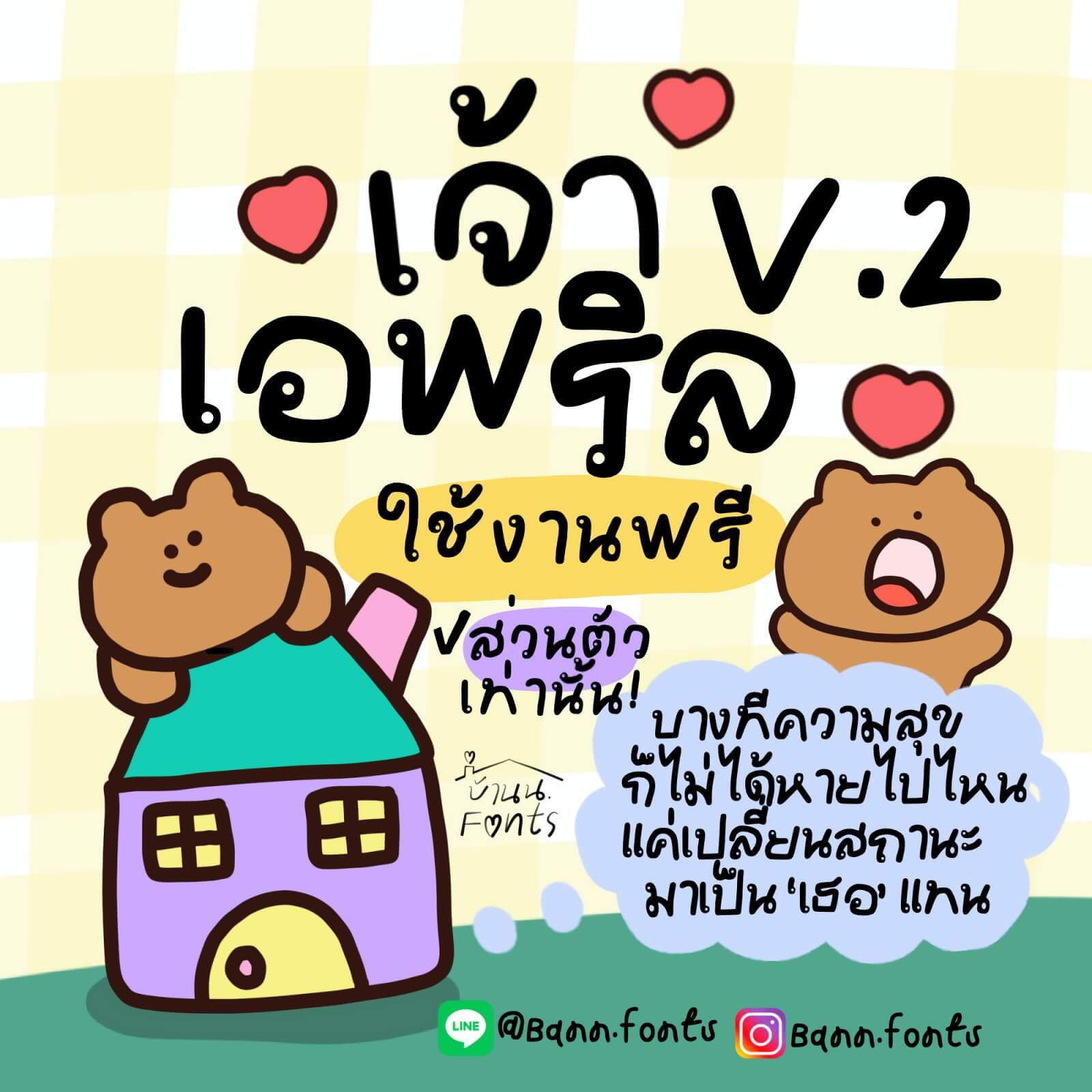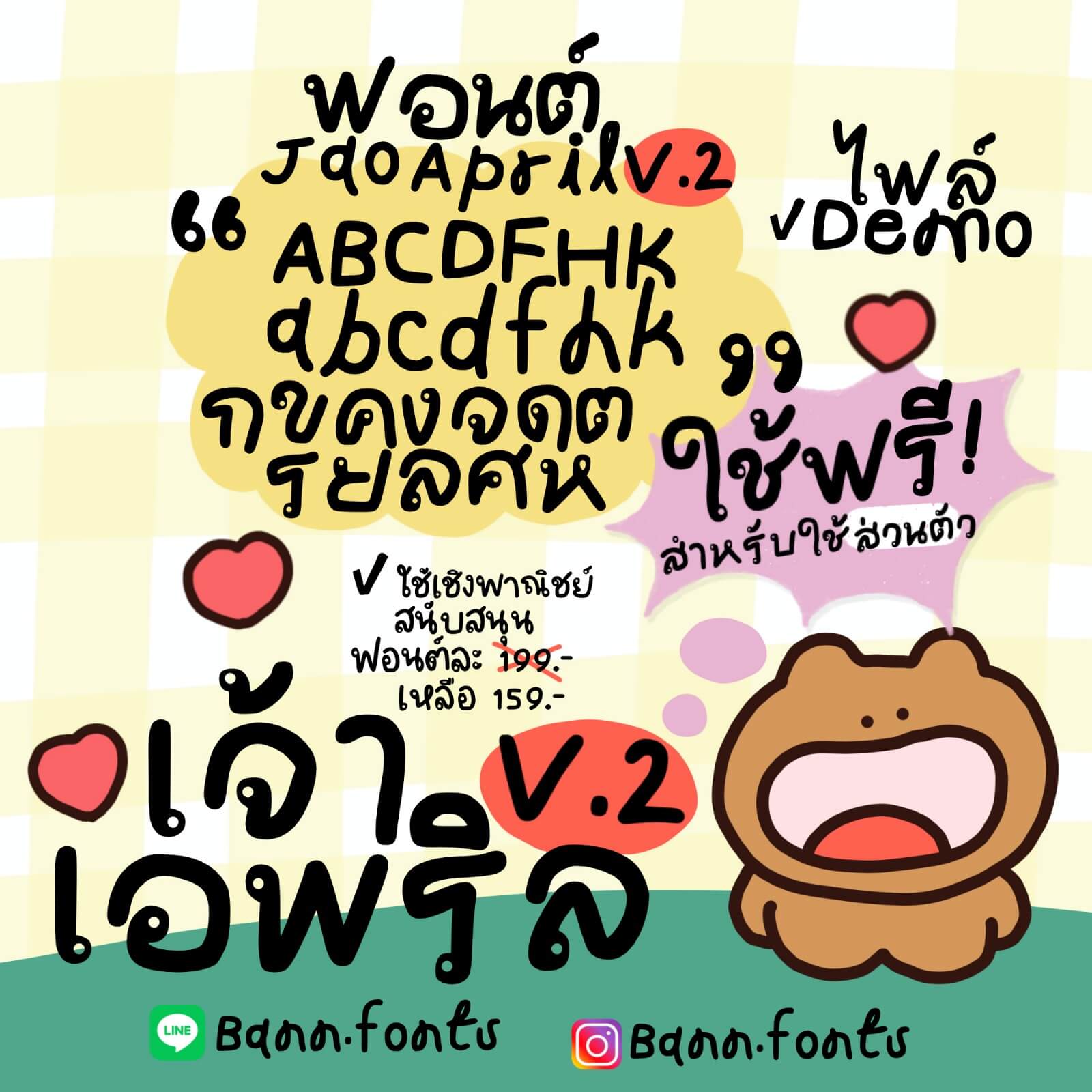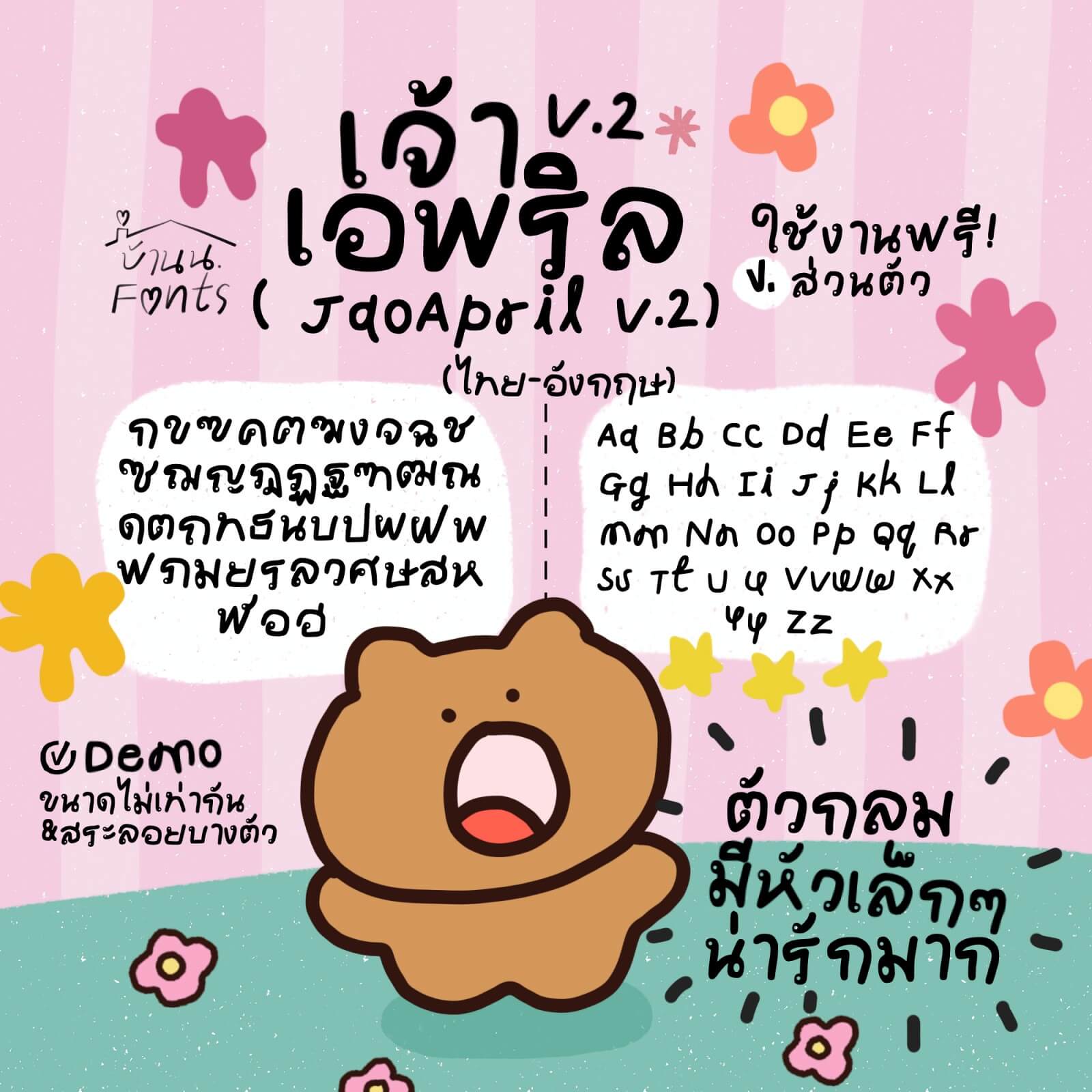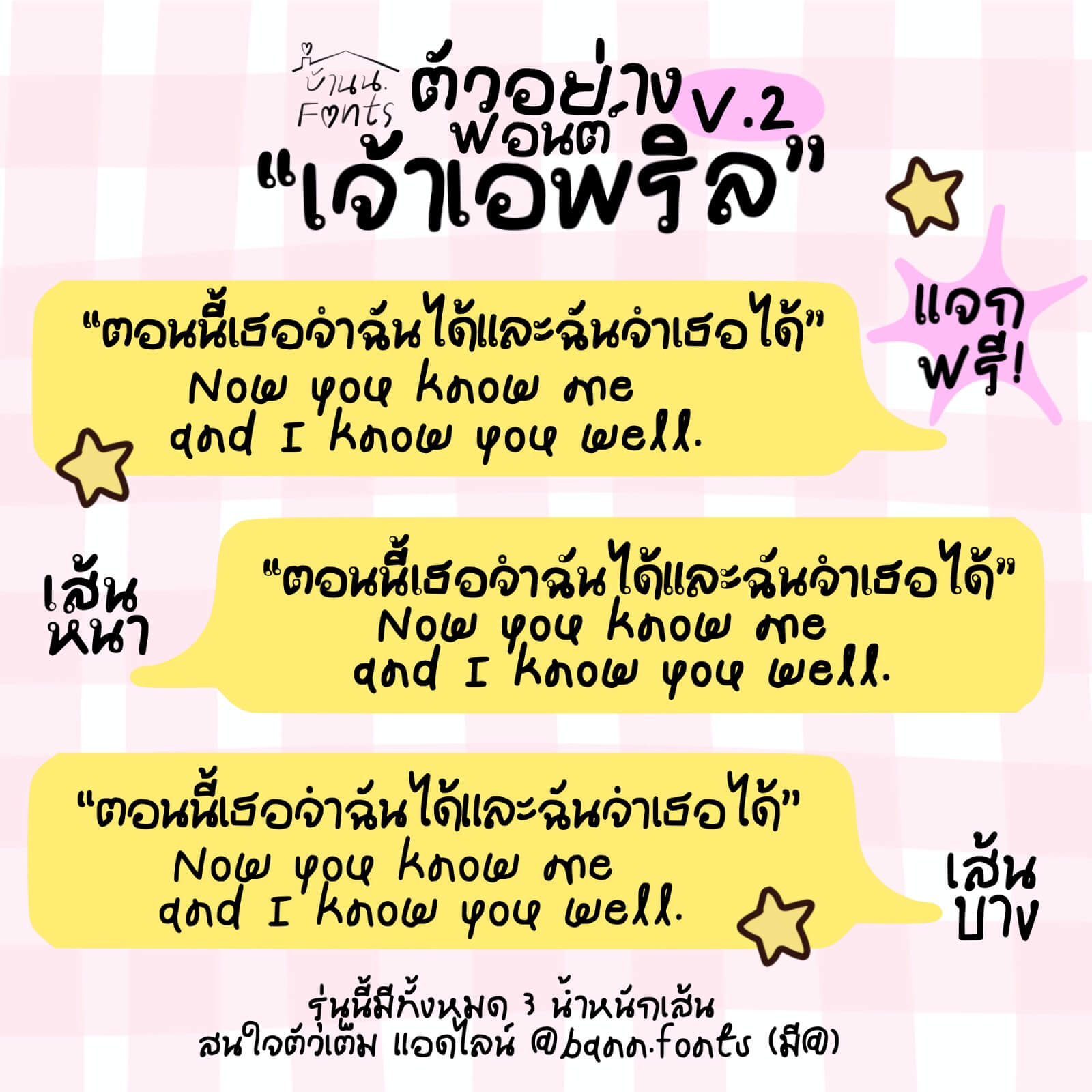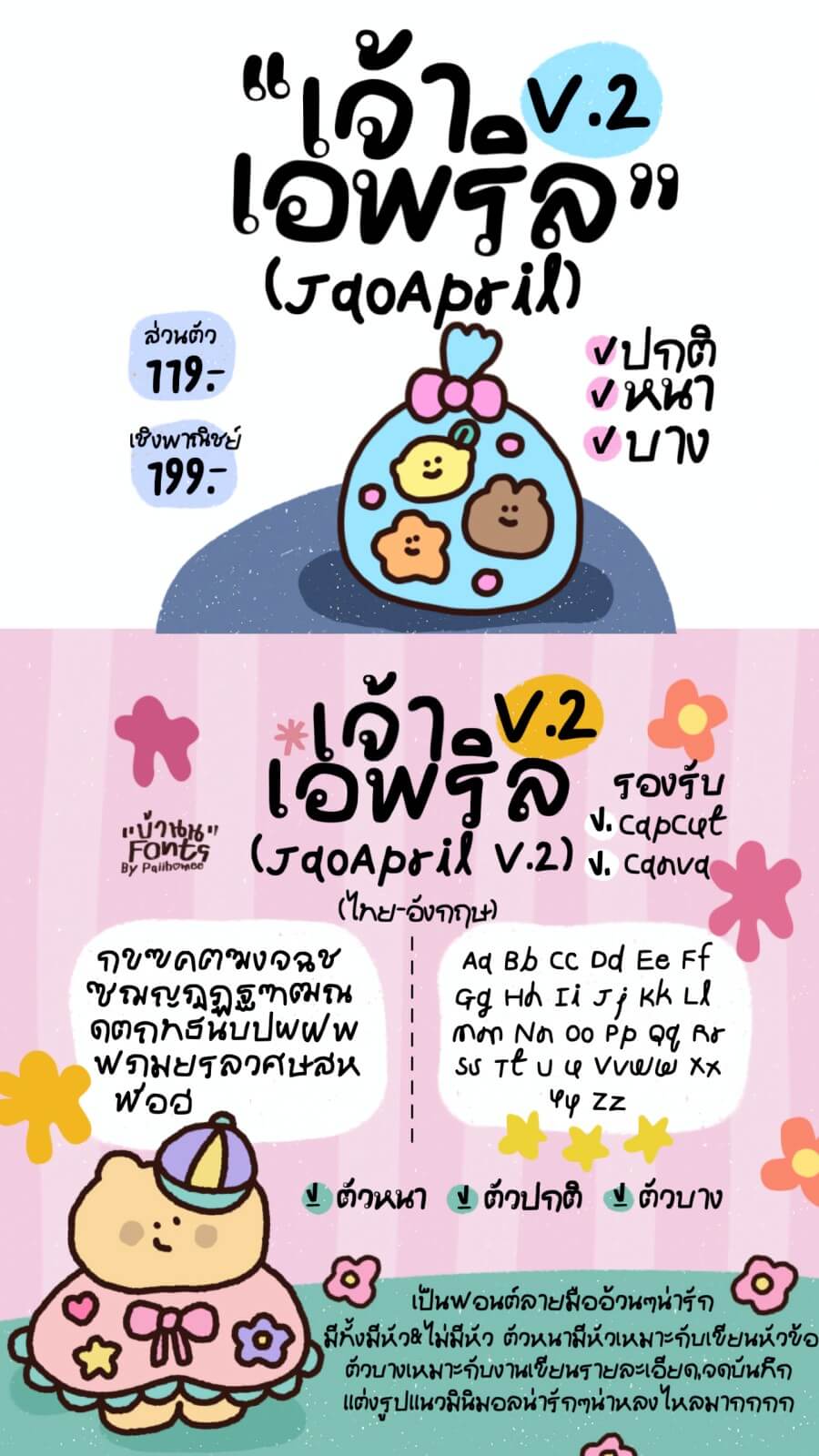
เจ้าเอพริล v.2 (JaoApril v.2)
ฟอนต์เจ้าเอพริล v.2 – แจกฟรี! สำหรับใช้ส่วนตัวเท่านั้น ฟอนต์น่ารัก มีหัว อ่านง่าย ทำคลิป แต่งรูป จดโน้ต จดบันทึก ส่งงานอาจารย์ มีติดเครื่องไว้เลย แนะนำค่ะ
- สระยังไม่ได้ปรับสมบูรณ์และน้ำหนักฟอนต์อาจแตกต่างกัน
- ไม่มีเลขไทย (๐๑๒๓๔๕๖๗๘๙)
ฟอนต์ : เจ้าเอพริล v.2 (JaoApril v.2)